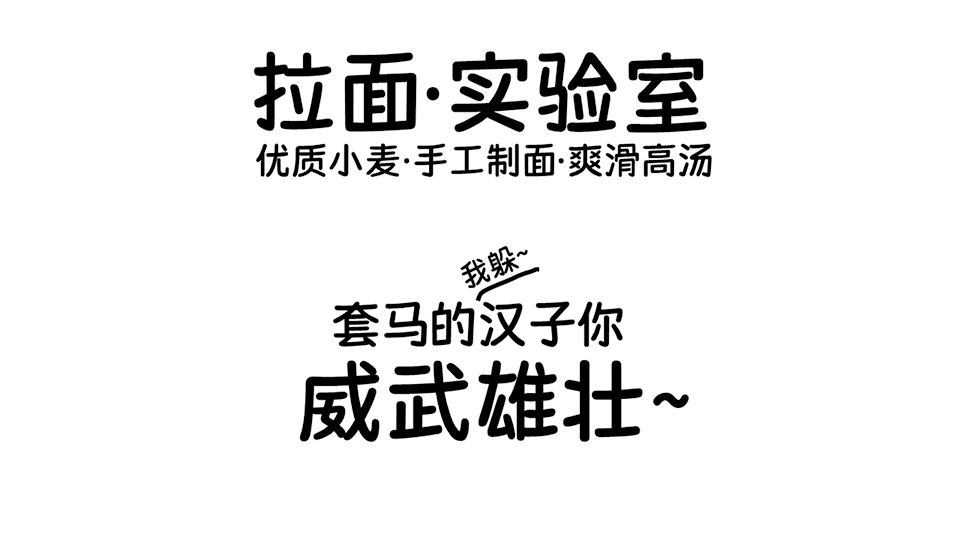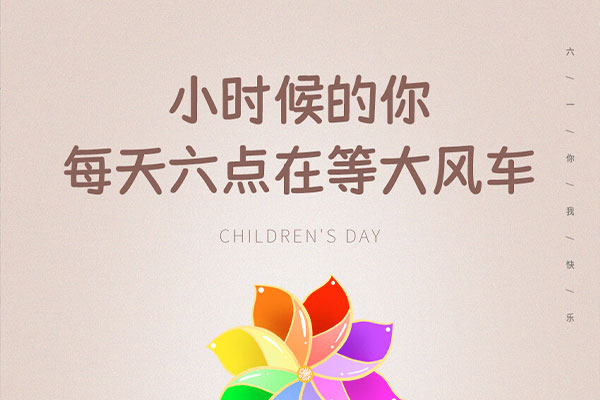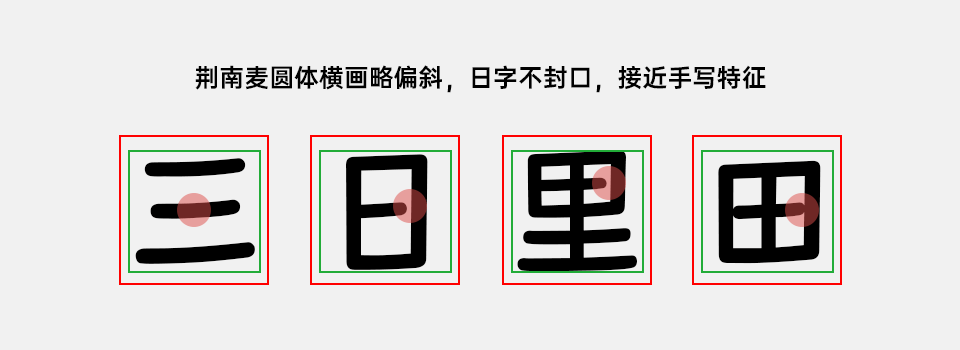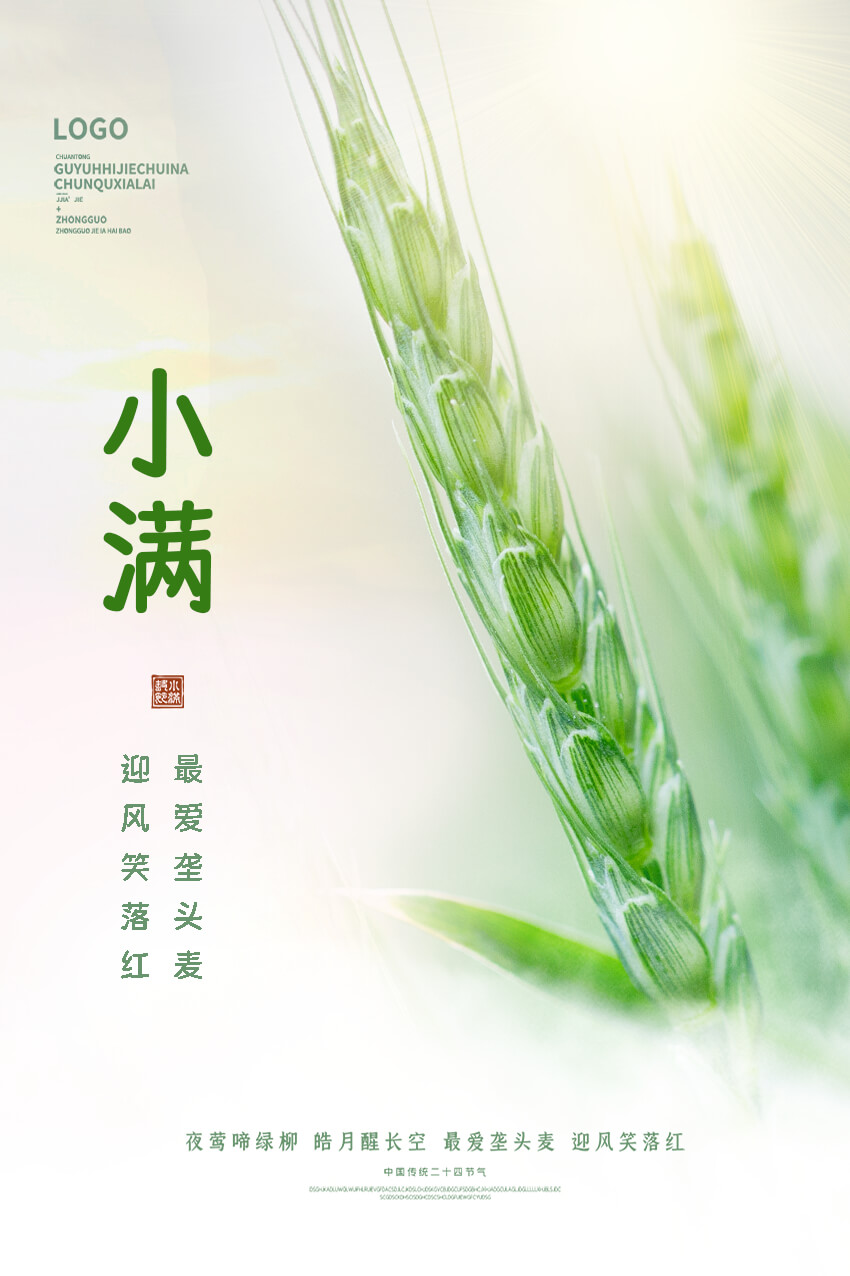
荆南麦圆体,是荆南字坊精心打造的第二款免费商用字体。而首款字体,则是备受喜爱的荆南缘默体。
今天,我们重点介绍一下荆南麦圆体。这款字体的设计灵感,来源于韩国一档综艺节目中出现的谚文字体。那种手写风格,流畅而圆润的笔画,给人们带来了十分可爱的感觉。这也是荆南麦圆体的独特魅力所在。
作为一款免费商用字体,荆南麦圆体在保持了手写风格的同时,也兼顾了易读性和美观性。无论是在包装、电商、漫画、影视综艺、游戏,还是各类商业海报和户外广告中,都可以灵活应用,让你感受到不同的文字表现力。
总的来说,荆南麦圆体是一款极具手写特色的免费商用字体。它将给设计师带来全新的创作灵感和文字表达方式,也帮助人们更深刻地理解到荆南字坊对于字体设计的执着与热爱。
荆南麦圆体萌系可爱的手写风格,字体每个笔画的粗细相同,两端圆润饱满,凸显可爱风格。虽是手写字体,笔画分明没有细小的连接,使字体更加清新俏皮。无论是做食品类还是母婴类,抑或是儿童类的设计都特别适合。
横画略偏斜,日字不封口,接近手写特征尾端圆润,横竖均一,保留趣味性的同时可读性高,也能适应屏幕显示。